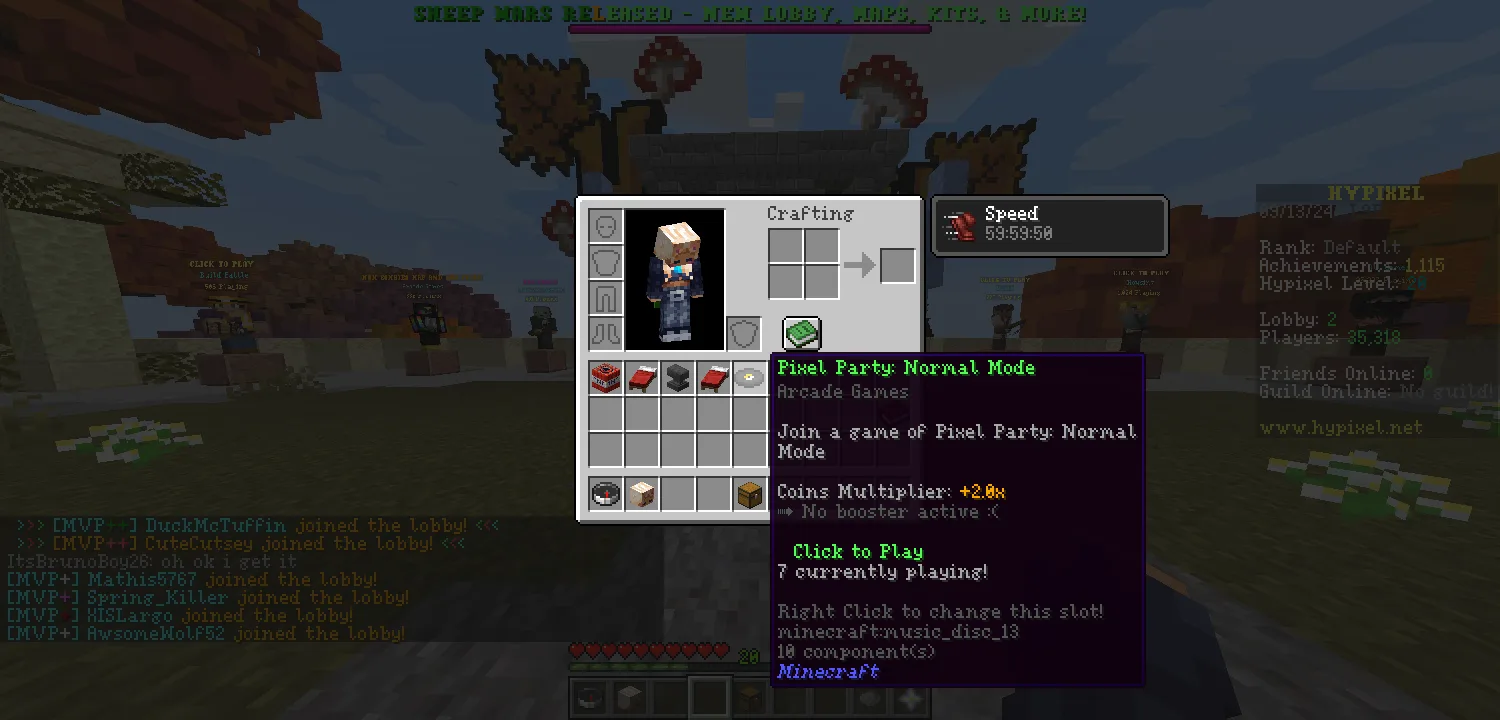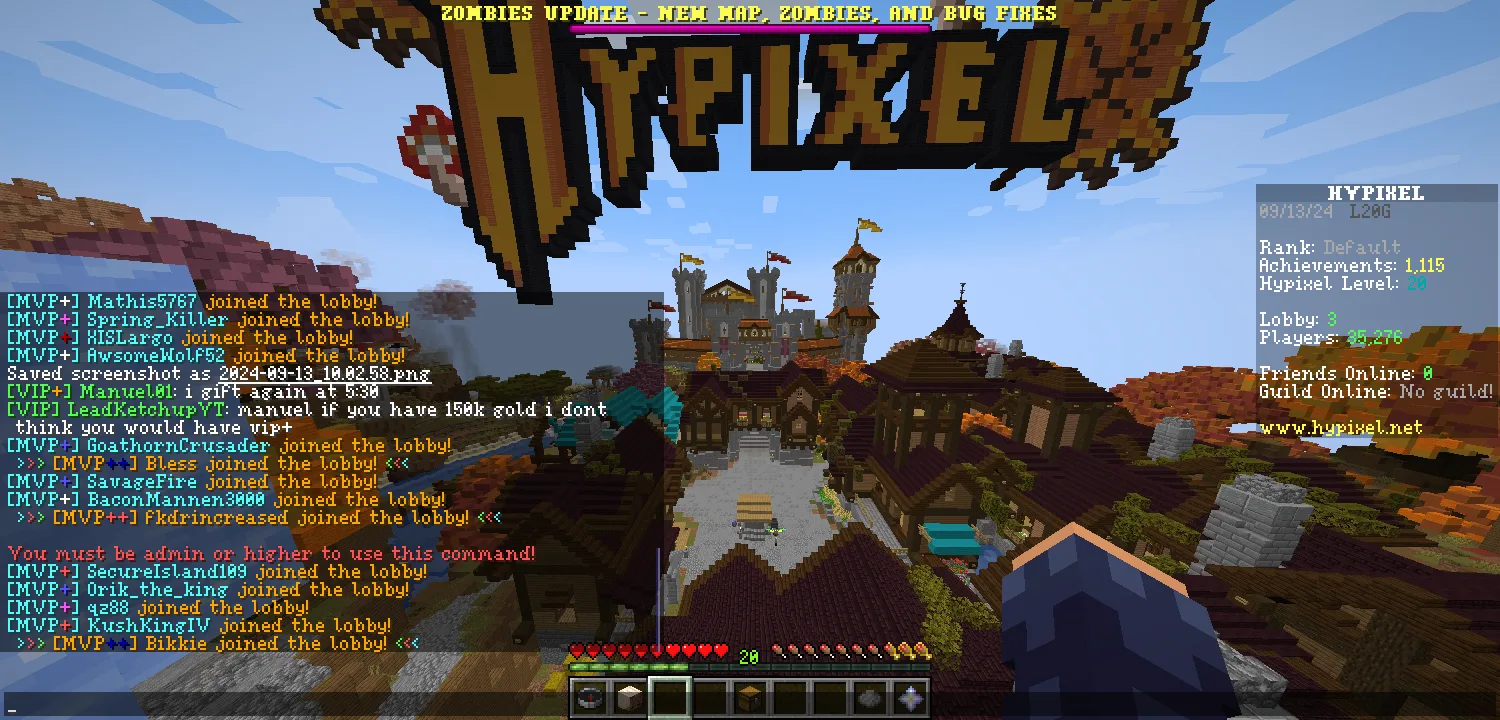
Jennie's Font
Тонкий шрифт с засечками для удобного чтения текста и отображения большего количества информации на экране.
Этот ресурспак заменяет стандартный шрифт Minecraft на более тонкий вариант с засечками, что делает текст более читаемым и позволяет размещать больше информации на экране. Шрифт отличается аккуратным и чистым дизайном, подходящим для тех, кто предпочитает минималистичный стиль. В настоящее время разработка сосредоточена на основном файле шрифта, включая множество символов, что обеспечивает постепенное улучшение визуального оформления текста в игре.